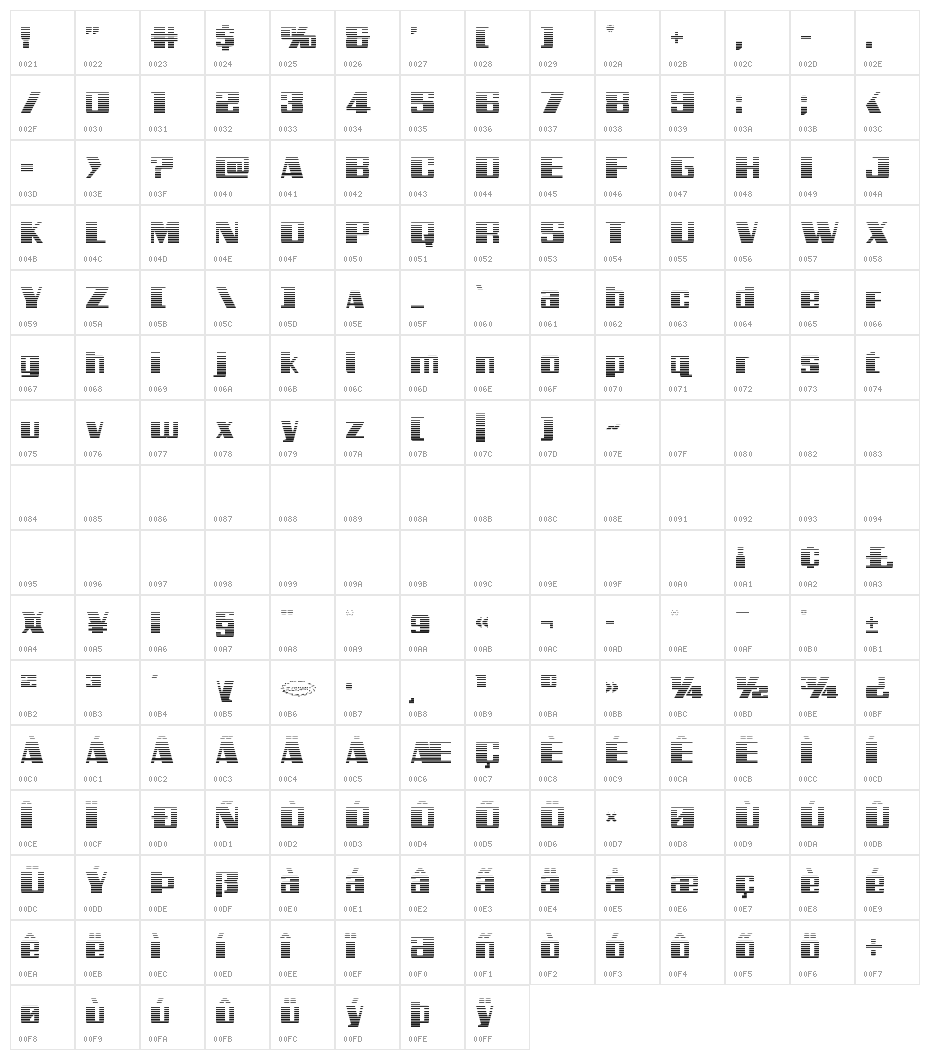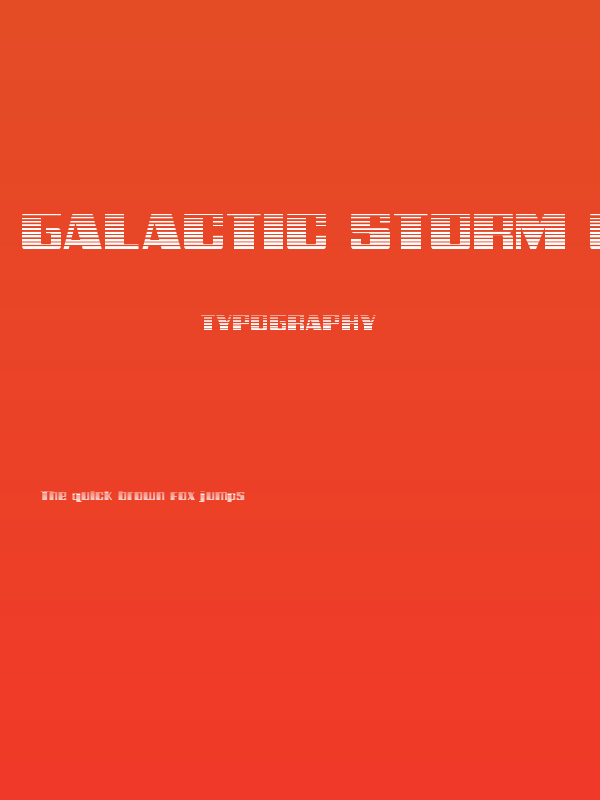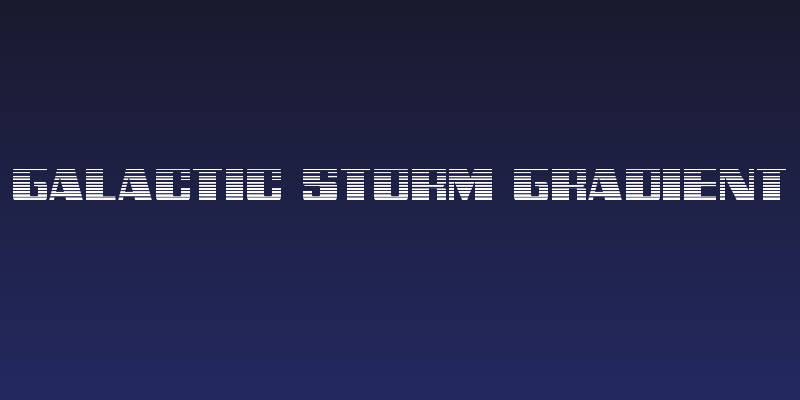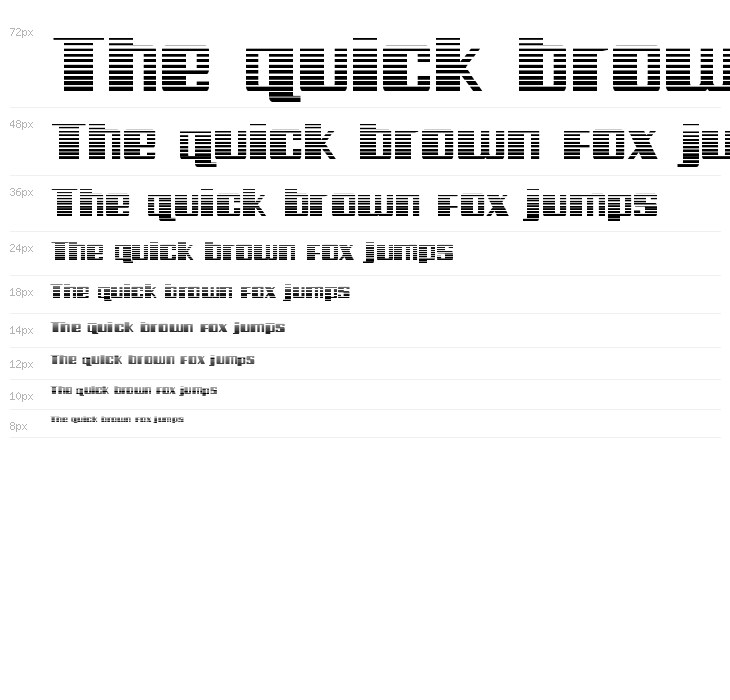
Galactic Storm Gradient Font
✎ Futuristic
| Vorgeschlagene Projekte | Ideal for sci-fi themed designs, video game titles, technology branding, and futuristic posters. |